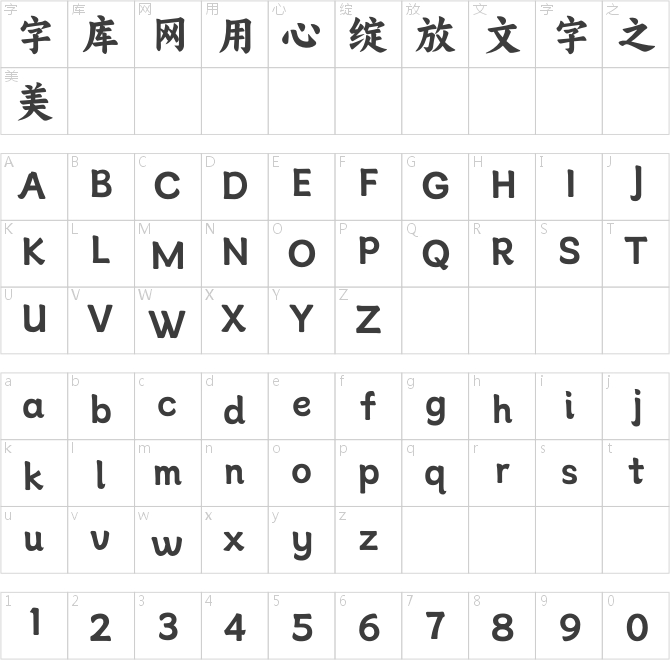
阿里妈妈东方大楷
阿里妈妈东方大楷是基于颜真卿的多宝塔碑算法生成并结合人力完成的一套字库,机器学习到了颜体的丰腴厚重之感,在笔画的描摹上做到了传统书法的收放起伏,规范了骨架、笔画,还原了书法中的落笔、转笔、藏锋、护尾等书写韵味,使整体更饱满、圆融、浑厚。
阿里妈妈东方大楷为中文简体字库,收纳的中文字符包括但不限于GB2312,共计6763个汉字;英文大小写(含全角、半角、合体字等)共105个;常用标点符号共175个,总计7043个字符。